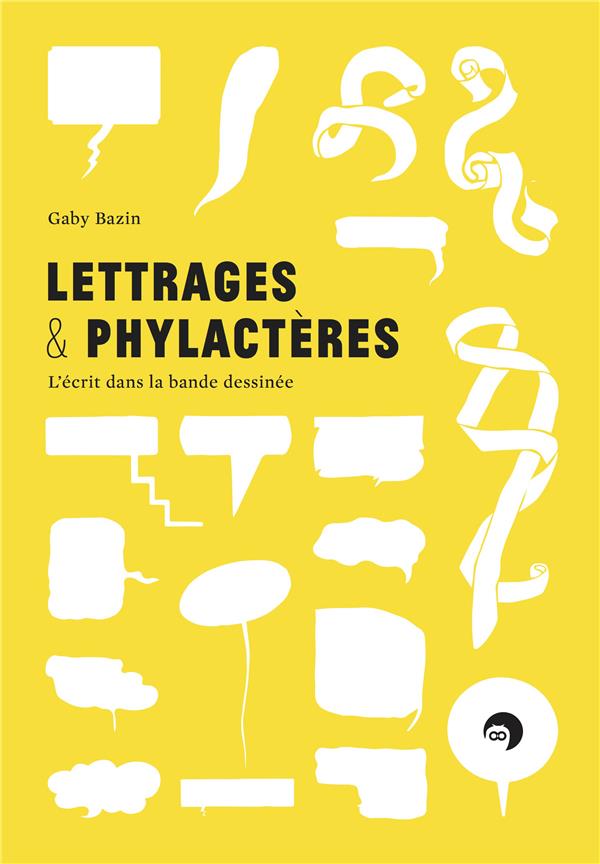
LETTRAGES ET PHYLACTÈRES
Livre neuf. Lettrages et phylactères. L'écrit dans la bande dessinée. Ce livre explore la notion généraliste de "rapport texte-image" dans les domaines du graphisme, du dessin de caractères, de l'illustration et de la bande dessinée. Le phylactère est l'objet privilégié par l'auteur pour présenter les différentes modalités de la mise en relation du texte et de l'image. Des vases grecs au lettrage des comics, de l'alphabet phénitien à la bande dessinée américaine, en passant par les enluminures, cet essai illustré propose divers dispositifs d'intégration de l'écrit dans le visuel.